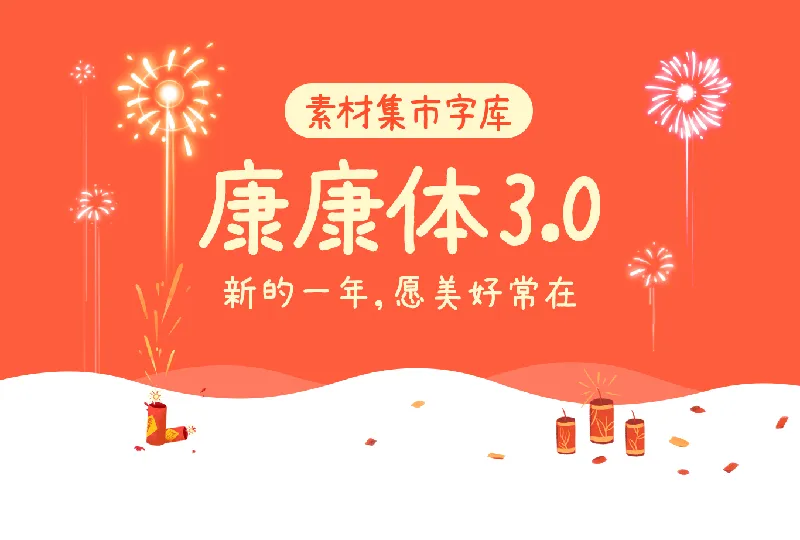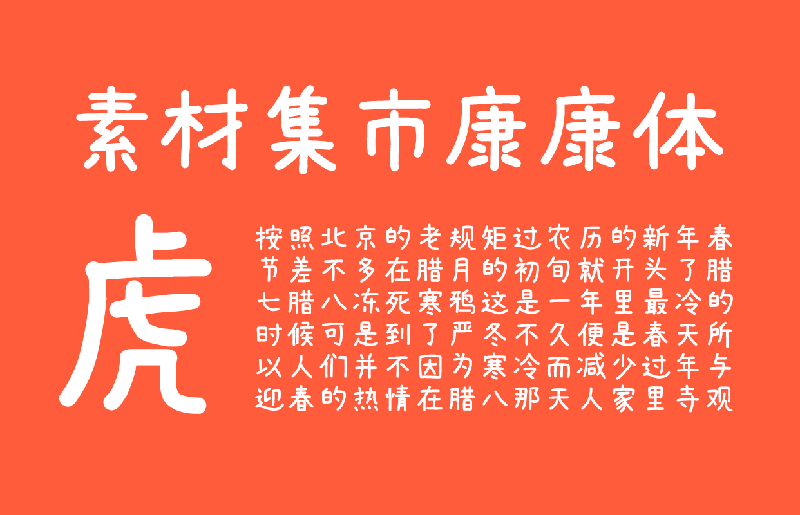
「素材集市康康体」是一款萌系可爱手写风格中文字体,距离素材集市康康体1.0 版本首次发布,已经过去了近两年,发布至今获得各界朋友的喜爱,在2021最后一天,终于迎来 素材集市康康体3.0完整版。
3.0版本由字集团队成员,时光羊独立完成,用了近6个月时间,在1.0版基础上增加5131个字,补齐GB2312-80编码字库,汉字和字符共计7754个。